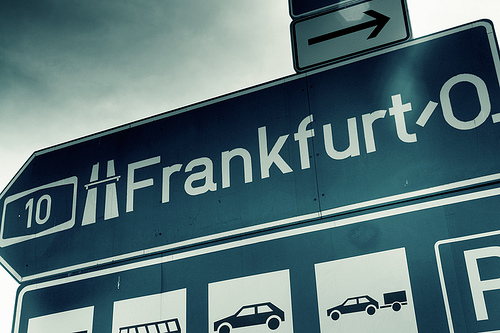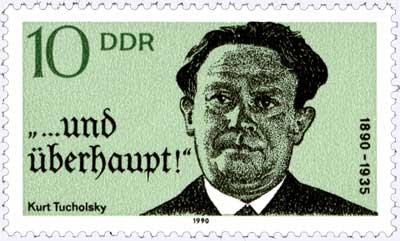
Frage zu die Schriften der DDR und BRD
Ich bin ein Student der UdK Berlin, aber ich komme aus Ausland. Jetzt werde ich ein Projekt machen, das über die Unterschiede zwischen DDR und BRD.Ich habe gesucht, es gibt viele typische DDR Schriften, die ich nutzen kann, aber für mich ist er schwierig ein passende typische BRD Schrift zu suchen. Kann man sagen, dass DIN ein ganz typische BRD Schrift ist? Oder habt ihr besseren Vorschlag für mich?
Vorschlag für typische BRD-Schrift: Helvetica … hatten viele bundesdeutsche Unternehmen als Hausschrift, Lufthansa z.B. (sag ich mal als West-Berliner, das Berlin-Layout von Stankowski war aber wohl Akzidenz Grotesk)
Woran ich mich auch sehr erinnere, dass man im täglichen Stadtbild in der Zeit, als es mit individuell gem,alten oder ausgesägten Schidermaler-Schriften langsam endete, und immer mehr benannte Schriftarten auftauchten, also Mitte der 1970er Jahre, die Schriftarten quer durch den Letraset-Anreibebuchstaben-Katalog fast allgegenbwärtig waren.
Hier sind auf den ersten Seiten siese Schriftarten verzeichnet:
Warum sollte die 1927 entstandene Futura nicht auch in der DDR genutzt wurden sein?
Ja, da hast Du nicht ganz unrecht. Möglicherweise auch ein Wackelkandidat wie die DIN. Aber ich würde meinen, dass sich unter den geometrischen eher die Schriften von Drescher in der DDR etabliert haben, z.B.:
oder
Typisches Futura-Beispiel wären die Bahnhofsschilder der deutschen Bahn vor Frutigers »Offensive«.
Warum sollte die 1927 entstandene Futura nicht auch in der DDR genutzt wurden sein?
Natürlich wurde sie das. Ich kenne sie noch aus dem Blei (Ost). Aber natürlich nicht annähernd so intensiv wie die Super, welche die DDR durch ihre Omnipräsenz wie kaum eine andere Schrift typographisch geprägt hat.
Vielleicht ist es gar nicht möglich die typische BRD-Schrift zu finden. Die DDR war eine Planwirtschaft und so gab es eben nicht zig verschiedene Schrifthersteller sondern eben Typo-Art. Da diese die Super-Grotesk im Programm hatte wurden diese dann auch reichlich genutzt und somit eine der typischen DDR-Schriften. In Westdeutschland konnten sich die Druckereien im freien Markt bedienen, wodurch es mehr Vielfalt gab aber eben nicht die typische Schrift entstehen konnte.
Man kann ja mal das Gedankenexperiment machen und eine typische DDR-Marken und die westlichen Marken nebeneinanderstellen. Im Osten war das typische Waschmittel „Spee“ (es gab noch ein paar andere z.B. Imi oder Milwa aber die verloren nach der Einführung von Spee schnell an Bedeutung) und im Westen: „Persil“, „Sunil“, „Ariel“, „Dash“, „Weißer Riese“, „Wipp-Expreß“, „Rei“, …
Aus deutscher Sicht bemerkenswert ist die Tatsache, wie unbefangen
die
Typografen in der DDR mit den gebrochenen Schriften umgegangen
sind. Auf Theater- und Kino-Plakaten, ja selbst auf politischen Plakaten
der Einheitspartei wurden bedenkenlos gebrochene Schriften eingesetzt.
Willberg berichtet in seinem Aufsatz »Vom falschen Image der Fraktur«
von einem Besuch bei Kollegen in der DDR.
Seine Frage, ob eine »Entnazifizierung der Fraktur« möglich sei, stieß
hier bei Studenten und Professoren auf Unverständnis. Während in der
Bundesrepublik der 70er Jahre ein so populärer Grafiker wie Klaus Staeck
gebrochene Schriften lediglich für seine satirischen Plakat-Schlagzeilen
»Mitbürger! Lesen macht dumm und gewalttätig«
(1975) oder
»Unternehmer! Macht euch die Erde untertan«
(1973) einsetzte, erschien
in der DDR die Auseinandersetzung mit der belasteten Vergangen-
heit dieser Schriften offensichtlich als ein Problem des Westens.
Der Kollege Martin Z. Schröder, der in (Ost-)Berlin seine Lehre
absolvierte, kommentierte diesen Sachverhalt sehr treffend wie folgt:
»Die ideologischen Zuschreibungen in Westdeutschland waren uns nicht geläufig,
wir unterschieden zwischen schöner und häßlicher Schrift, nicht zwischen guter
und böser.«
Albert Kapr, Professor in Leipzig und weltweit anerkannter Gutenberg-
Forscher, bestätigte mir angesichts eines Besuches der HBK Braunschweig
im Jahr 1983, daß die Grafiker der DDR, was den Einsatz der Fraktur
beträfe, keinerlei Beschränkungen unterworfen seien.
Zahlreiche Bücher aus der DDR, die in Fraktur oder Schwabacher
gesetzt waren, mögen dafür als Beleg dienen.
Da hätten wir ja schon zwei Punkte, die in der durchideologisierten DDR weniger ideologisch und pragmatischer abgehandelt wurden als in der Bundesrepublik: Fraktur und Kernkraft. ;-)
Futura und Super unterscheiden sich so klar voneinander, daß die Futura durchaus als westliche Schrift gelten darf, allerdings nicht auf Deutschland begrenzt. Der Mangel an Futura und Gill wurde so stark empfunden, daß manche Grafiker sie, etwa für Buchumschläge oder Plakate, von Hand zeichneten.
… Der Mangel an Futura und Gill …
Die Gill hatten wir aber sogar als Monotype-Matrizen, also praktisch unbegrenzt verfügbar (was natürlich noch nichts darüber sagt, wie breit sie tatsächlich verwendet wurde).